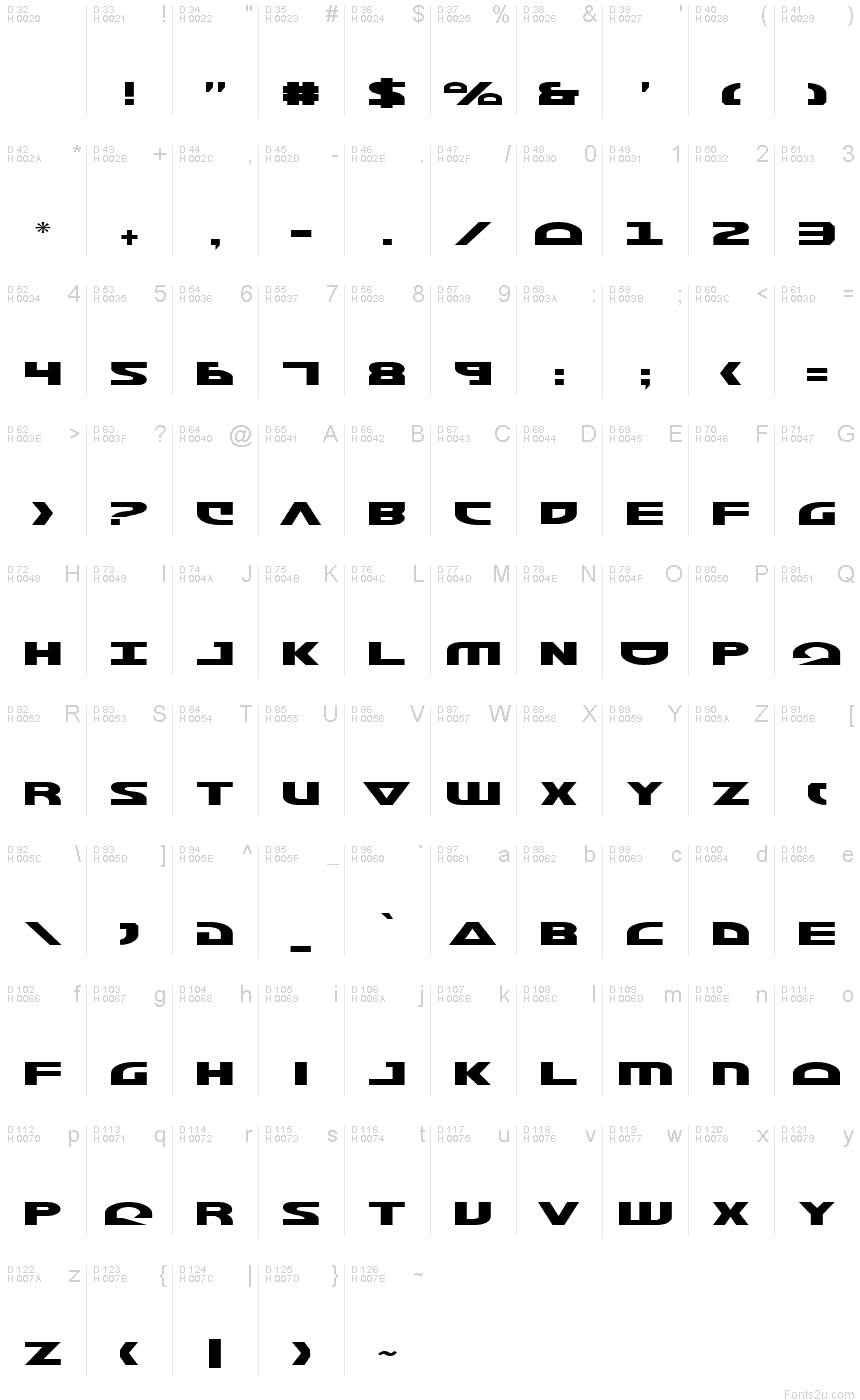
Morse NK
Morse NK di Iconian Fonts è un font display techno gratuito, caratterizzato da ampie forme nere con aperture dai lati dritti e intagli interni arrotondati. Il lettering ricorda una serie di moduli di segnalazione compatti, donando al design un ritmo orizzontale basso che risulta più codificato ed elettronico che semplicemente geometrico.
Questa silhouette compatta ha una presenza tale da adattarsi a titoli di giochi, poster sci-fi, grafiche musicali, elementi per streamer e intestazioni di brand dove un sans serif standard risulterebbe troppo neutro. Le righe brevi traggono particolare vantaggio da questa struttura incisa, poiché le fessure ripetute e le tacche curve creano una pulsazione visiva costante lungo la parola, piuttosto che un semplice blocco di testo.